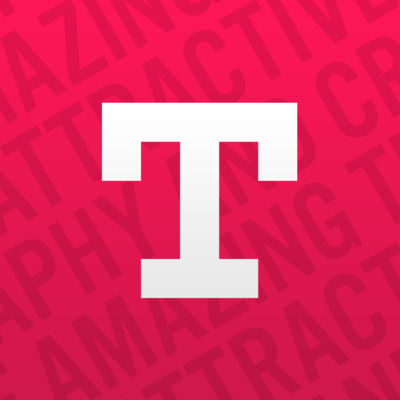
Die Entwickler von Typorama verbessern ihre Anwendung kontinuierlich. Nun gibt es ein empfehlenswertes Update.
Neben der Konkurrenz von Word Swag (App Store-Link) hat auch Typorama (App Store-Link) auf meinem iPhone und iPad einen festen Platz gefunden, wenn es darum geht, Bilder und Schriften ansehnlich zu gestalten. Zitate, Badges oder Sinnsprüche lassen sich mit den oben genannten Anwendungen schnell und einfach gestalten, speichern und auch mit Freunden oder in sozialen Netzwerken teilen. Typorama ist kostenlos im App Store erhältlich und kann über einen In-App-Kauf von 4,99 Euro mit allen Features freigeschaltet werden, optional lassen sich auch einzelne Funktionen für kleineres Geld erstehen. Die 111 MB große Anwendung erfordert iOS 8.0 oder neuer und verfügt über eine deutsche Lokalisierung.
Typorama, der Name deutet es schon an, bietet die Möglichkeit, Bilder mit Texten zu verschönern. Insgesamt gibt es knapp 50 unterschiedliche und zufällig generierte Text-Stile, die sich typografisch unterscheiden. Der Text ist selbstverständlich editierbar, zudem lässt sich die Deckkraft und die Stärke der Umrandung einstellen. Die angebotenen Schriften und Texte werten Bilder in wenigen Handgriffen auf.
Ebenfalls mit dabei sind neun einfache Foto-Filter, verschiedene Overlays wie Herzchen, Lichteffekte, Schnee und mehr, auch lassen sich Fotos bezüglich der Helligkeit, Kontrast, Sättigung oder Sichtbarkeit anpassen. Fertige Fotos lassen sich in maximaler Auflösung und vielen Wallpaper-Formaten für iPhone und Co. exportieren, optional ist das Teilen direkt bei Facebook, WhatsApp, Twitter und Co. möglich, die lokale Ablage wird ebenfalls unterstützt.
Manueller Zeilenumbruch für noch mehr Design-Freiheiten
Mit dem just erfolgten Update auf Version 1.4.4 von Typorama können sich insbesondere Freunde der Advents- und Weihnachtszeit freuen: So gibt es in der Hintergrundbild-Auswahl nicht nur einige vorgefertigte Weihnachts-Motive, sondern auch eine festliche Schriftart. Damit lassen sich weihnachtliche Grüße und Sprüche stilvoll und dem Anlass entsprechend mit wenigen Schritten kreieren.
Auch ein Manko der App, das ich immer als ärgerlich eingestuft habe, wurde mit dem Update auf v1.4.4 behoben: Die maximale Zeichenzahl des einzufügenden Textes wurde seitens der Entwickler nun auf 350 Zeichen erhöht. Auch das Design, sprich die Länge bzw. Größe des Textes kann jetzt dank eines optimierten manuellen Zeilenumbruchs noch besser gesteuert werden. Mit diesen Features hat Typorama auf meiner Typografie-Bestenliste definitiv wieder die Nase vorn.